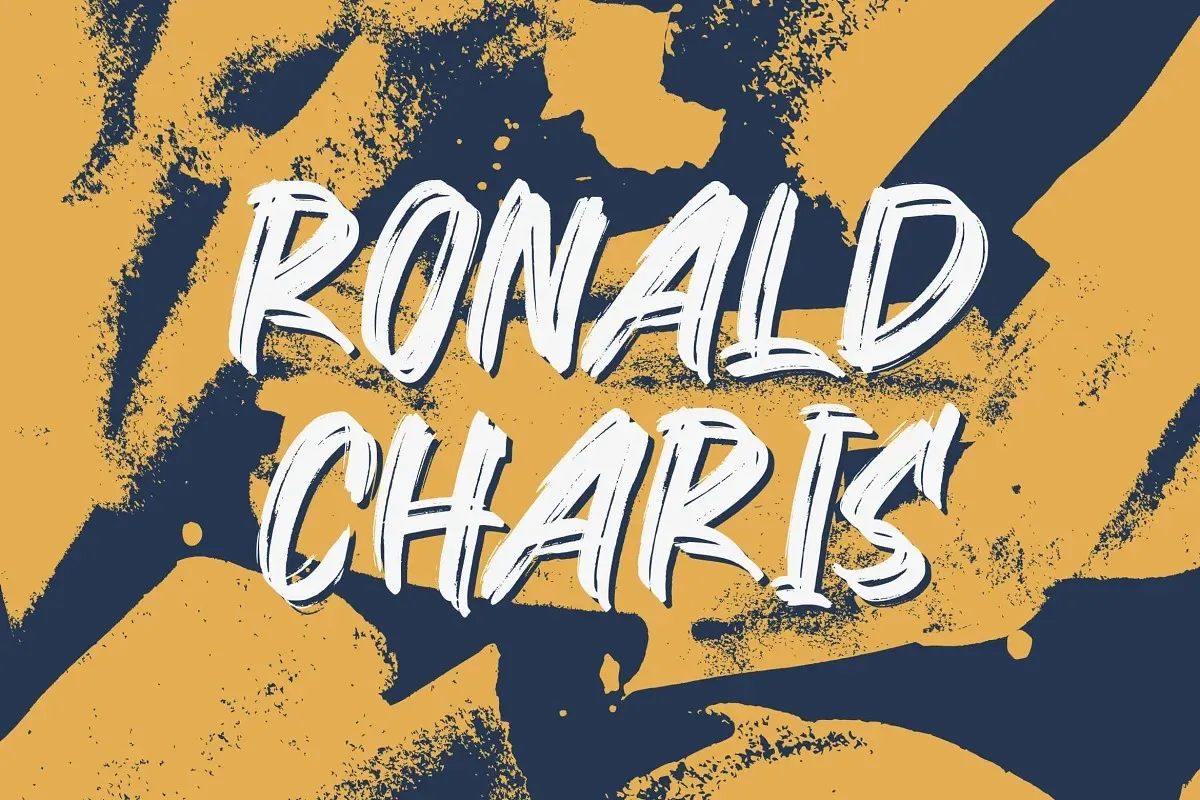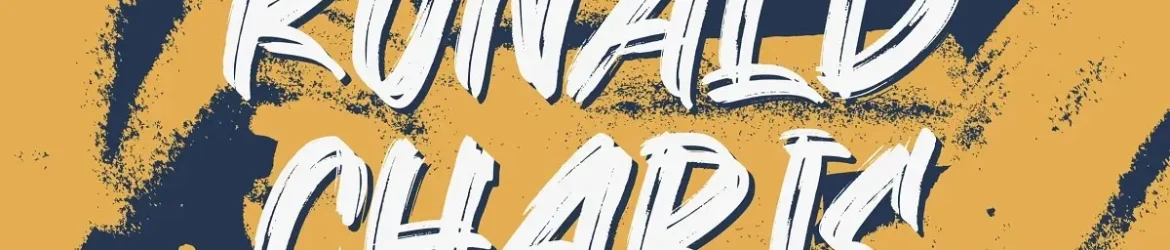
A ‘Ronald Charis Font’ é uma escolha perfeita para quem busca uma fonte script brush que captura a essência do verão e do sossego. Desenvolvida pelo font designer StringLabs, essa tipografia é ideal para quem deseja um visual descontraído e autêntico, com traços livres e fluidos. Suas linhas leves e delicadas transmitem uma sensação de serenidade e despreocupação que se ajusta perfeitamente aos ambientes de verão, seja em posters ou logos, capas de livros, camisetas personalizadas, embalagens ou qualquer outro tipo de design gráfico. Com a ‘Ronald Charis Font’, você pode criar designs únicos e incrivelmente bonitos para uma ampla gama de aplicativos. Este é um verdadeiro alívio visual perfeito para quem está procurando por uma fonte que transmita elegância e modernidade ao mesmo tempo em que mantém o espírito descontraído da estação mais quente do ano.